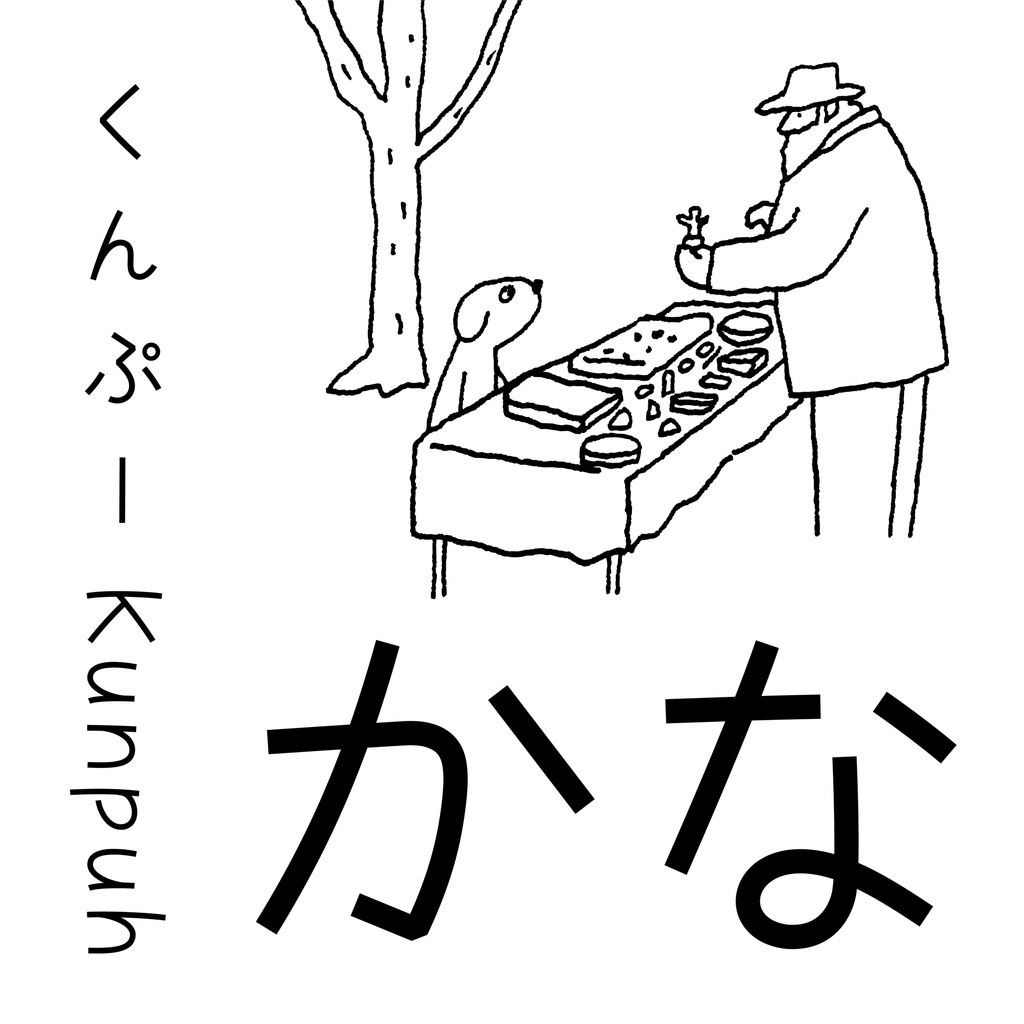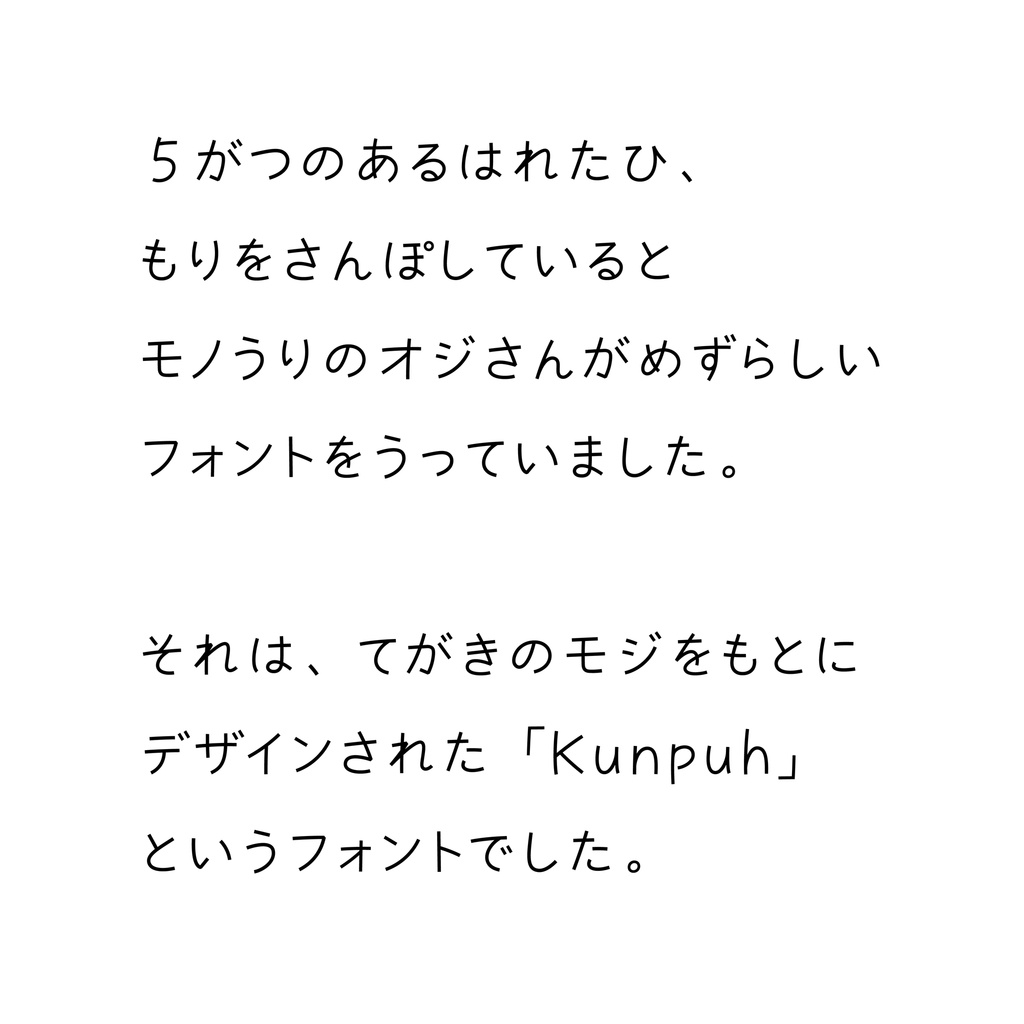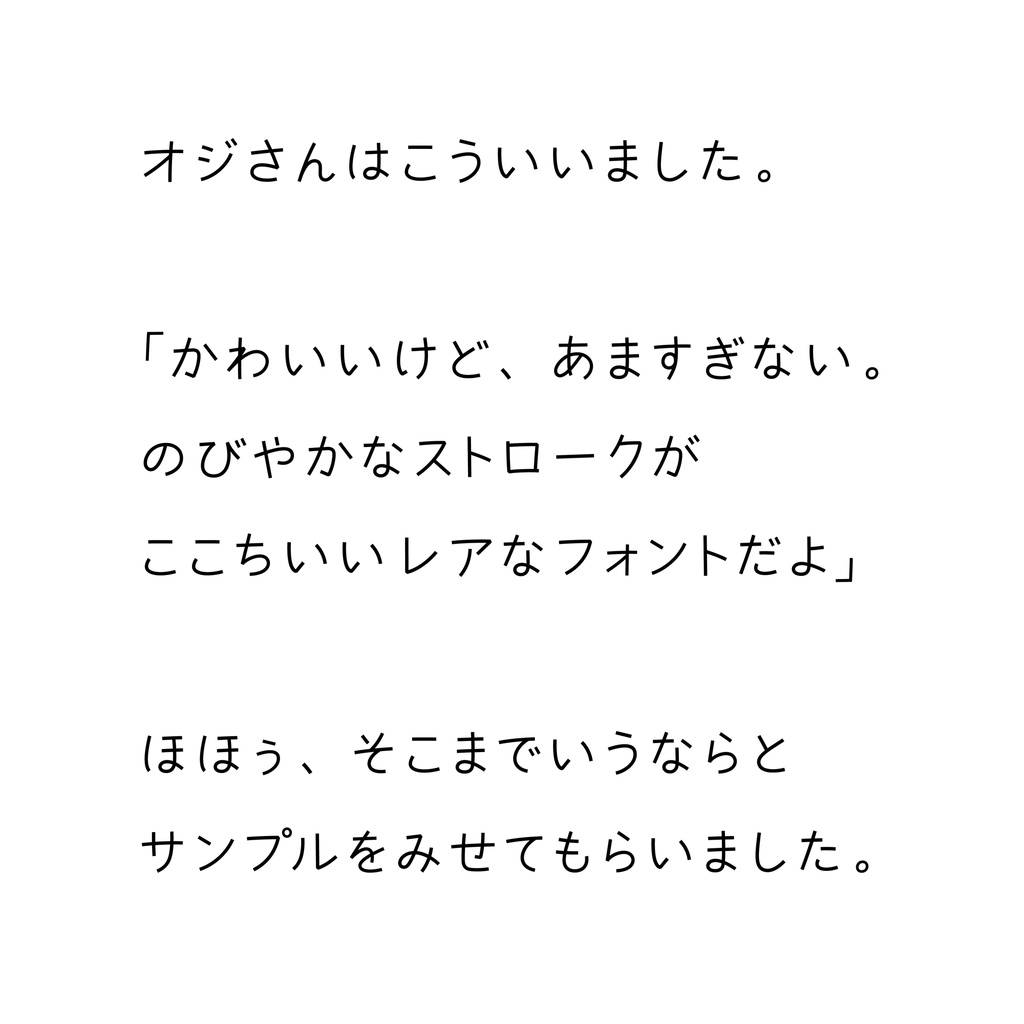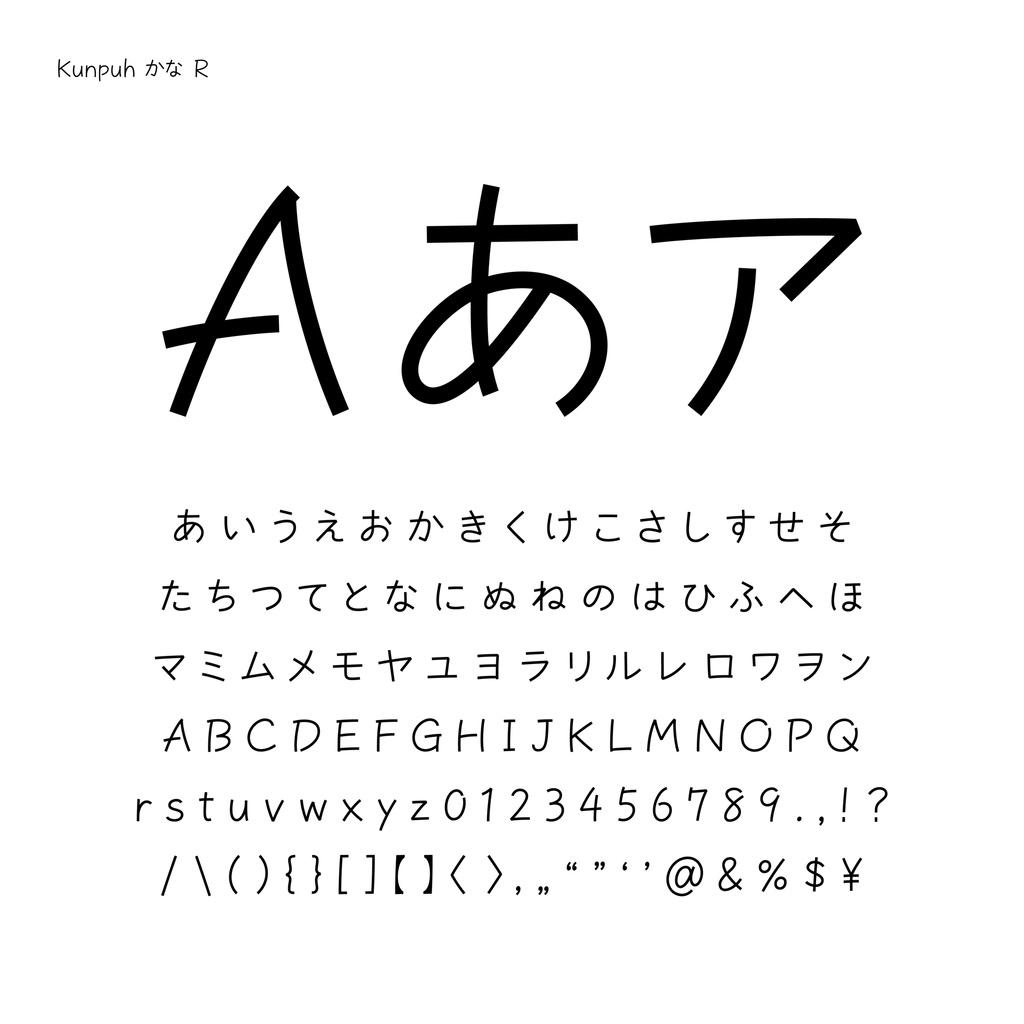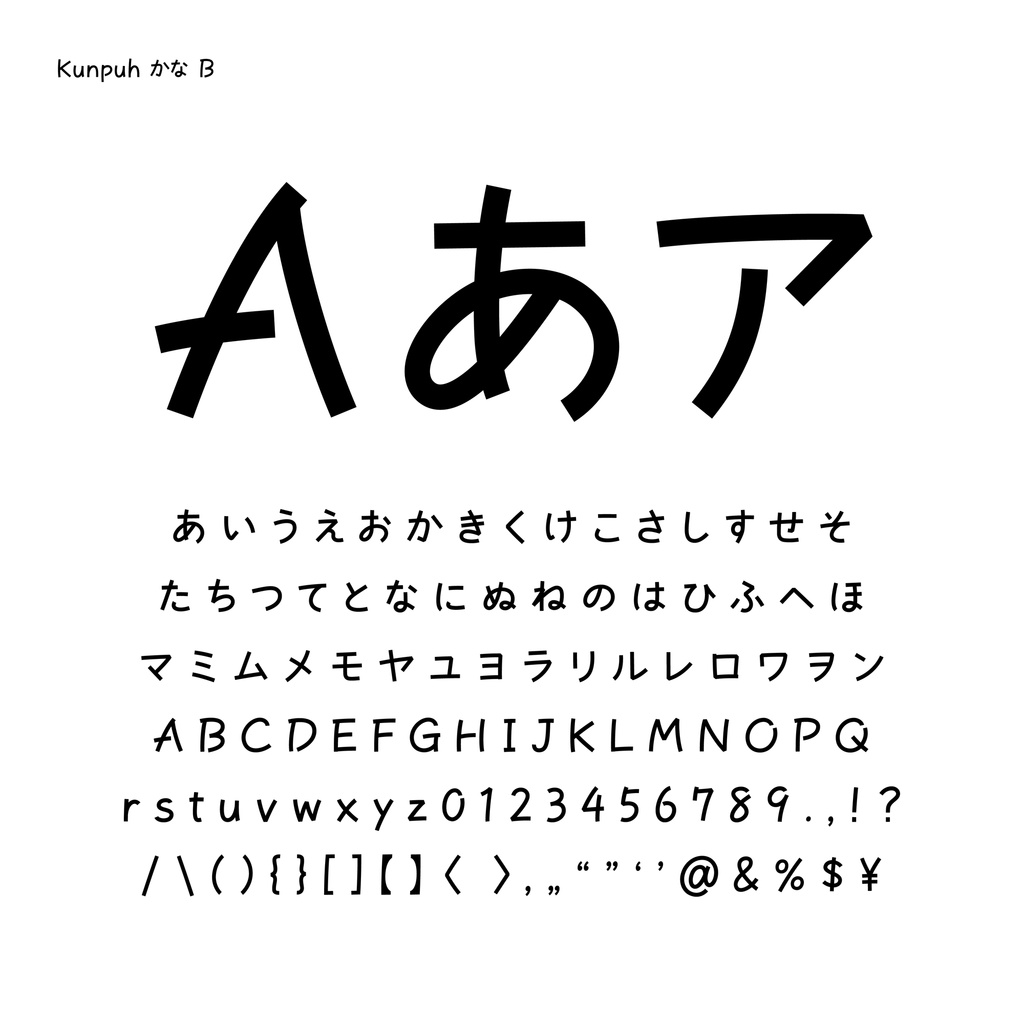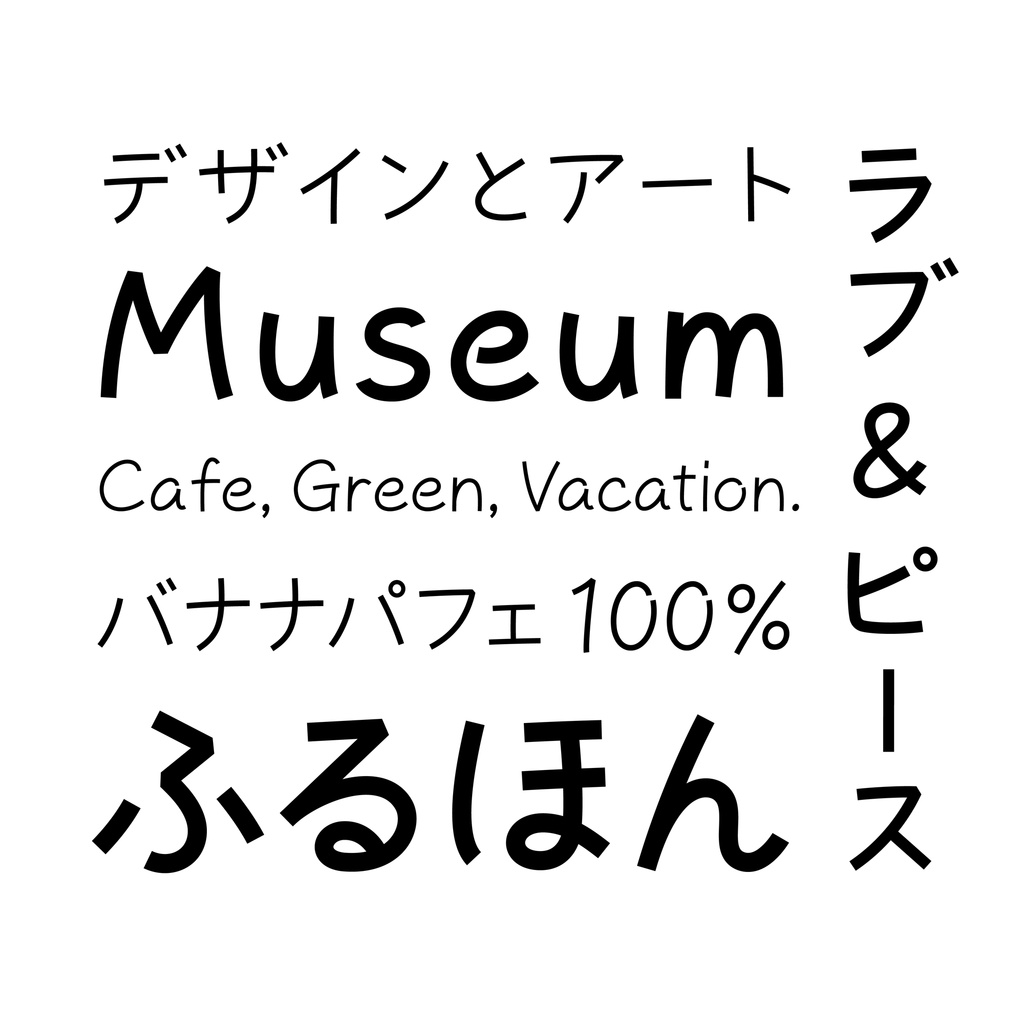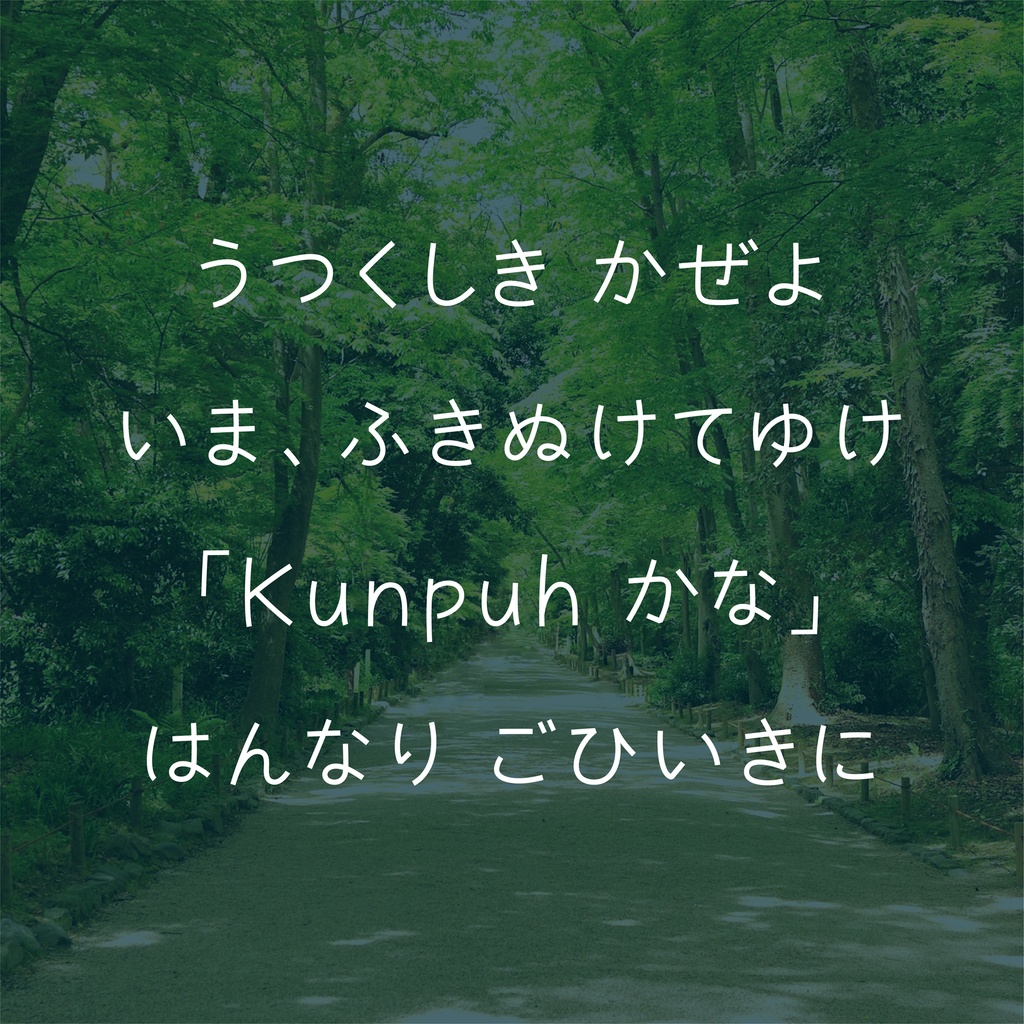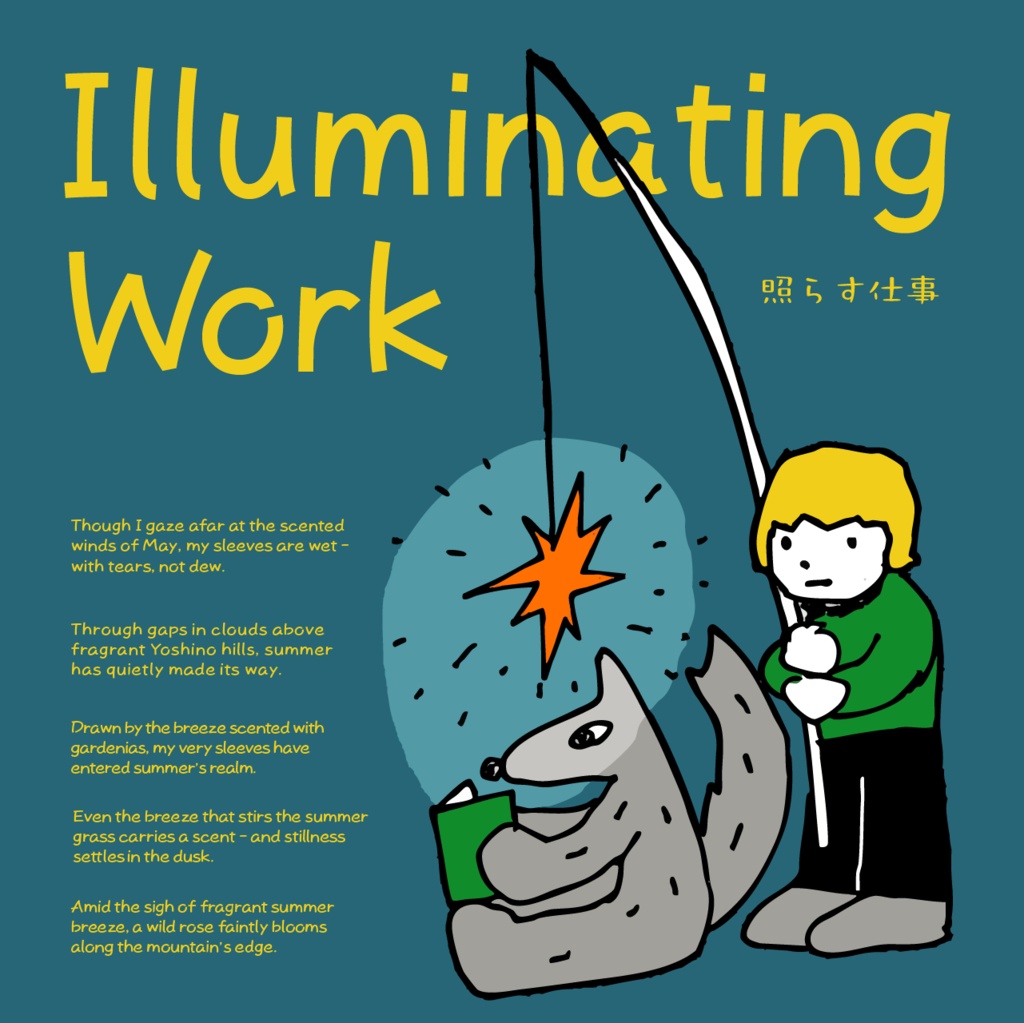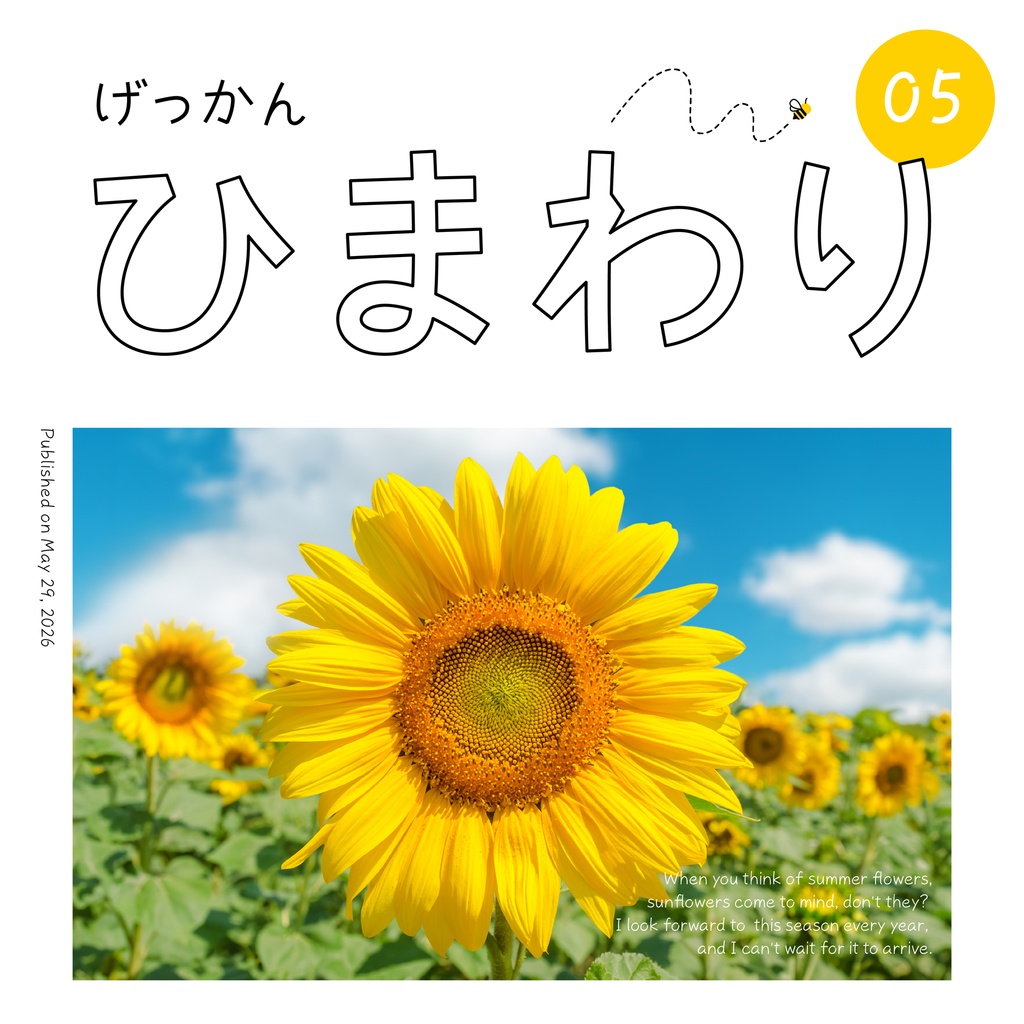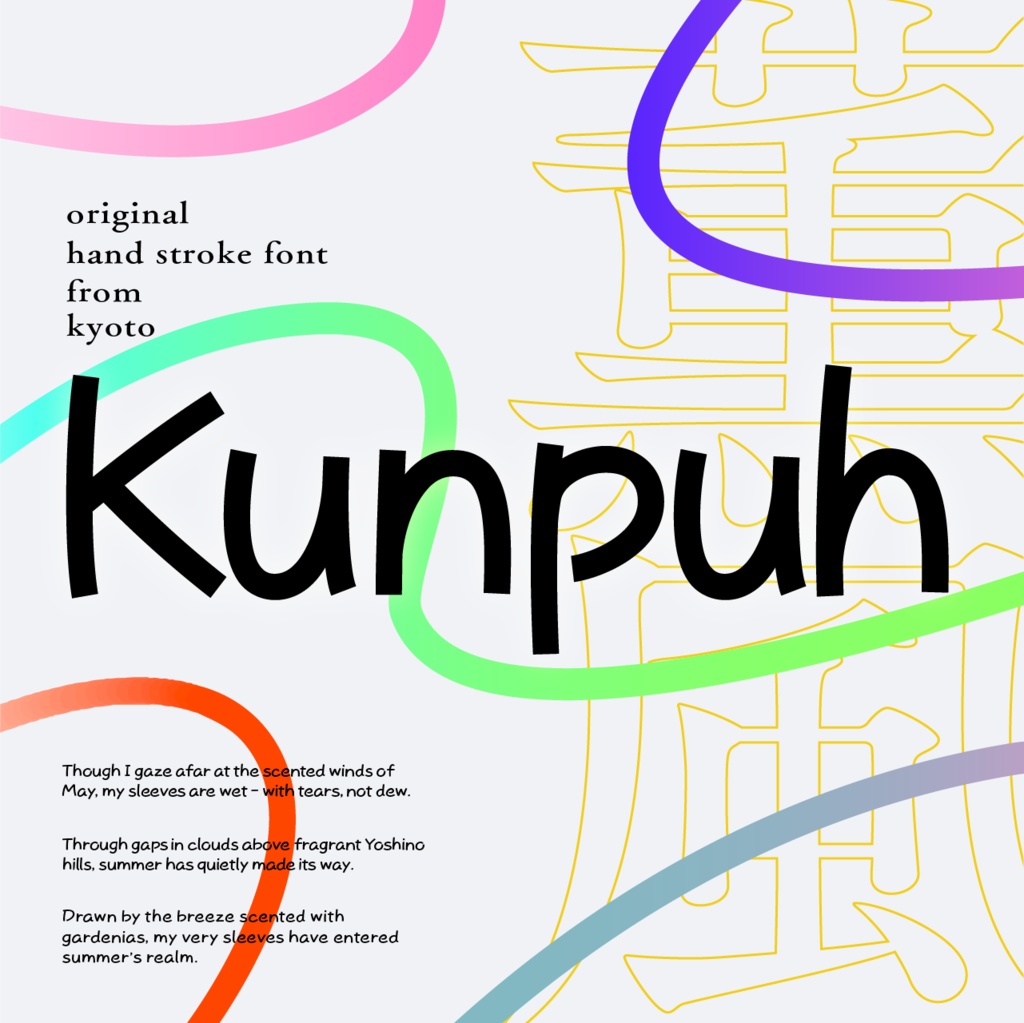
「Kunpuh かな」手書き風・かなフォント
◎かわいいけれど甘すぎない ◎伸びやかなストロークとぬけ感が心地いい 手書き風フォント「Kunpuh(クンプー)」は、手書きの文字をベースにディスプレイ用のフォントとしてデザインされました。 2026年5月、新たにひらがな・カタカナを追加し「Kunpuh かな」としてリニューアル! 初夏の季語である「薫風」に由来したネーミングで、イントネーションは「シャンプー」と同じです。 [ 薫風 / くんぷう:初夏、新緑の間を吹いてくる心地よい風。]